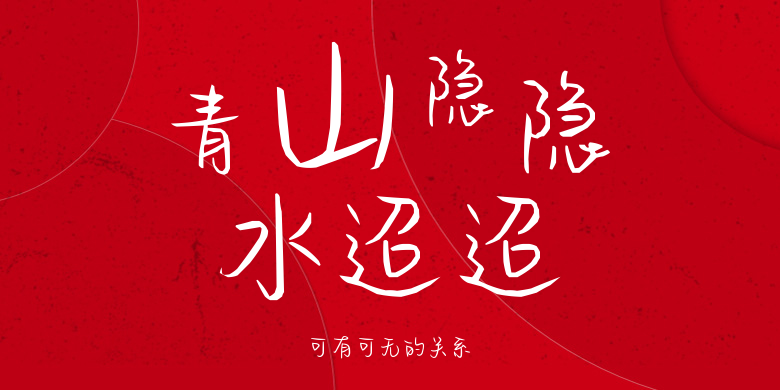
可有可无的关系
可有可无的关系,这款字体结构工整、笔画清晰,兼顾美观与易读性,适用于标题、正文、海报、包装、LOGO 等多种场景。字形优雅稳定,风格百搭耐看,适配日常排版与创意设计,让文字呈现更舒适、更具质感。可有可无的关系一笔一画,皆是细节,以均衡的比例、流畅的线条打造舒适视觉体验,字形端正大气,风格简约现代。无论是商业设计、品牌宣传还是日常排版,都能轻松驾驭,让文字更有格调与力量。可有可无的关系字体下载。